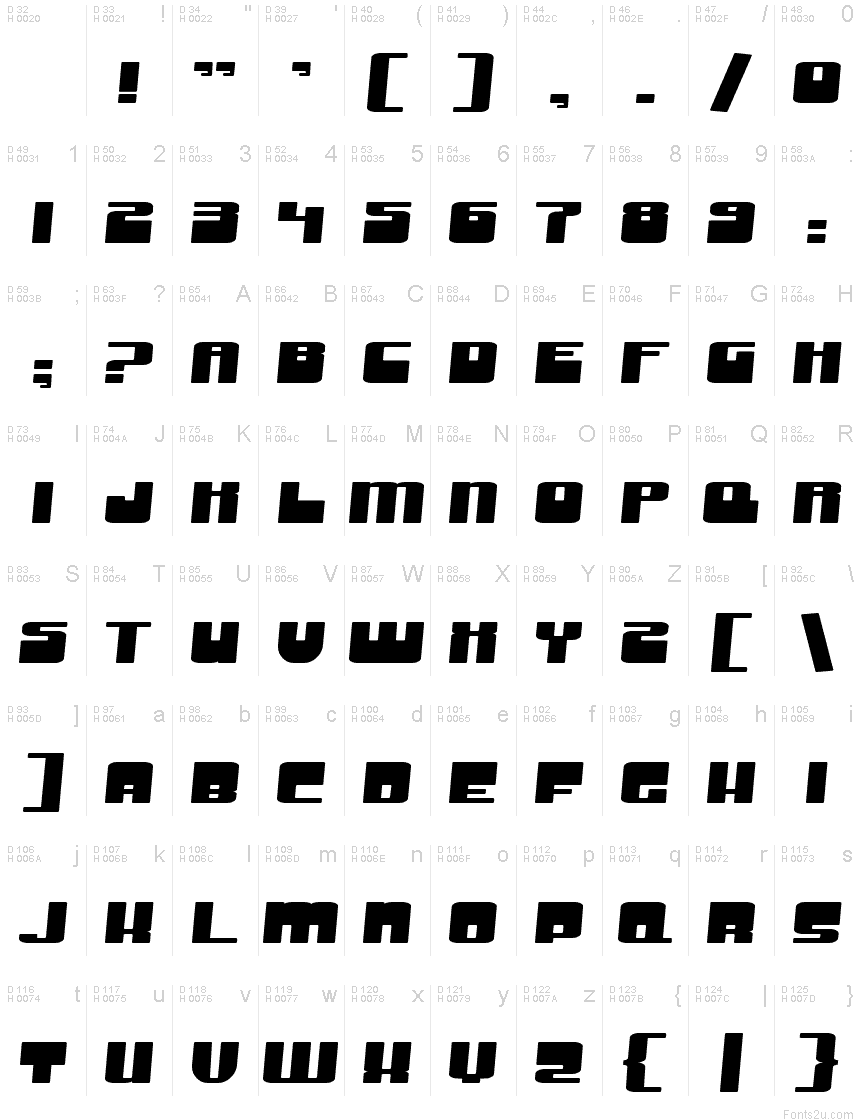
Groove Machine Expanded od Shywedge to darmowy, klimatyczny krój displayowy. Jego wyjątkowo szerokie litery przypominają grube winylowe naklejki naciągnięte na stronę, a pochylenie do przodu sprawia, że każde słowo wygląda, jakby wślizgiwało się w rytm. Masywne krzywizny i ciasne światła nadają mu wyrazisty, niemal gumowy charakter – jest głośny, ale płynny, jak idealnie podkręcona linia basu.
Dzięki Groove Machine Expanded nagłówki natychmiast nabierają retro-futurystycznego klubowego klimatu, którego nie da się przeoczyć. Świetnie sprawdza się na ulotkach imprezowych, plakatach muzycznych, okładkach albumów, w brandingu eventowym, miniaturach na YouTube oraz odważnych grafikach na merchu. Ten darmowy font błyszczy, gdy jest użyty w dużym rozmiarze i ciasno złożony; w tekście głównym połącz go z czystym, neutralnym krojem bezszeryfowym, aby pozwolić literom nabitym rytmem przejąć główną rolę.